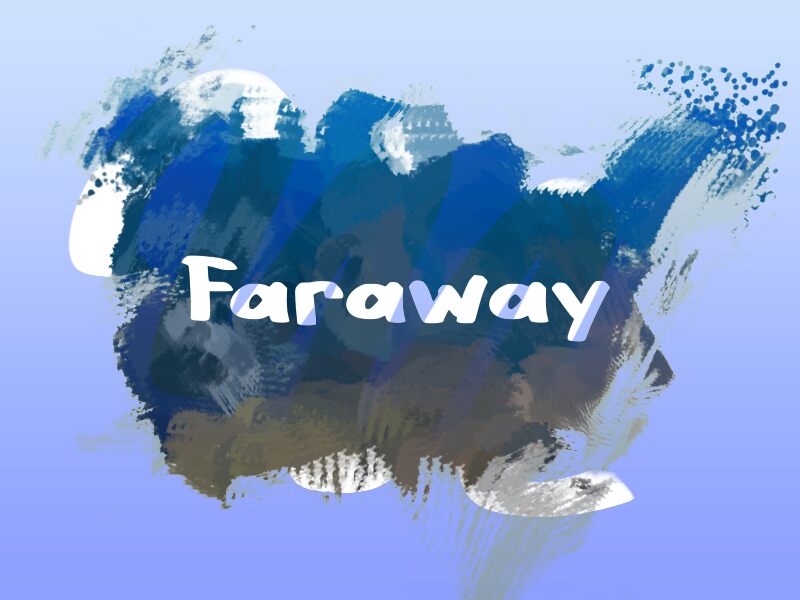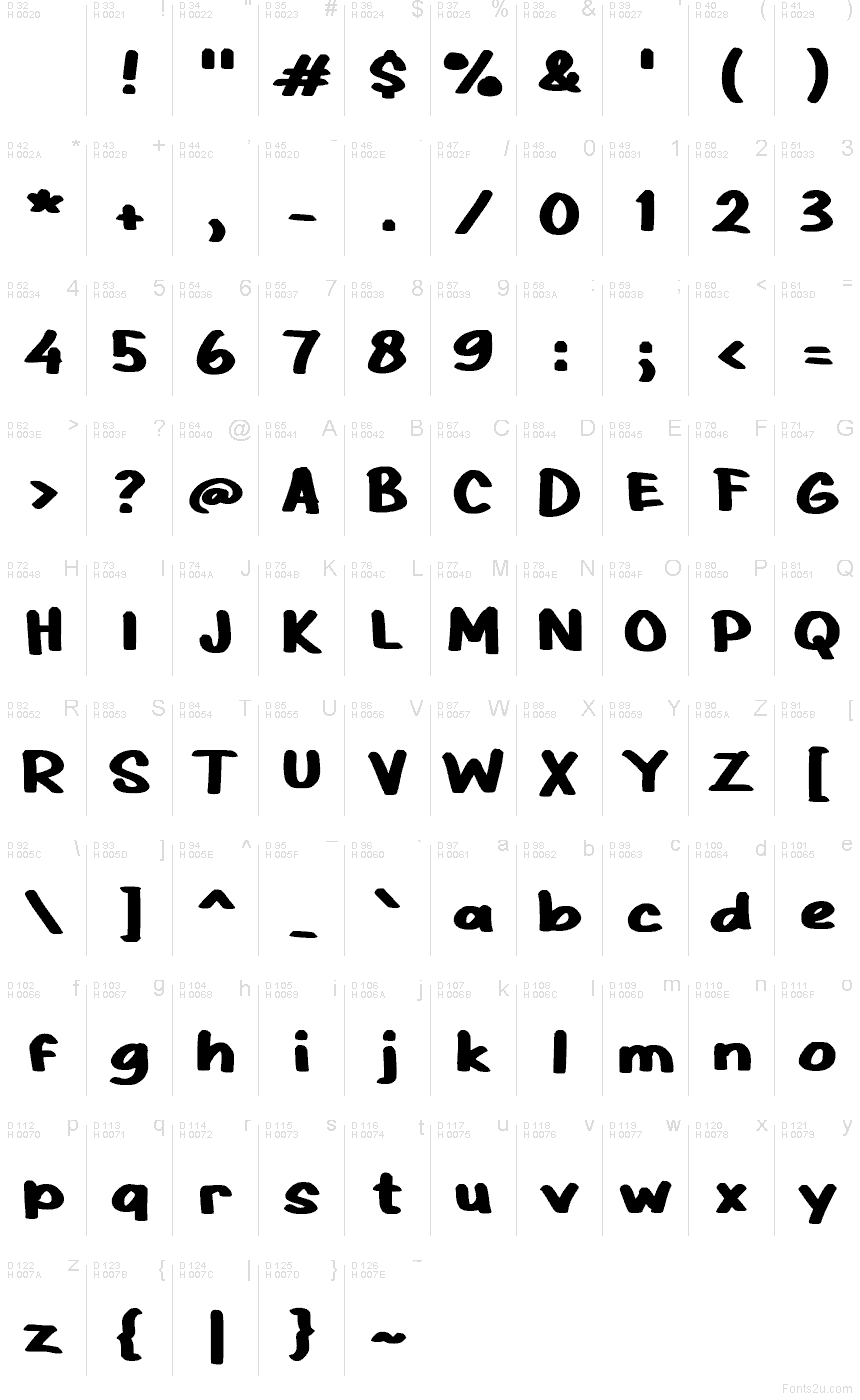
Faraway
Faraway от Wep — это бесплатный рукописный шрифт, массивный и с лёгким «мультяшным» характером. Буквы выглядят мягкими и живыми благодаря толстым скругленным штрихам, слегка неровным формам и естественной небрежности, которая не дает тексту выглядеть слишком строгим или «компьютерным».
Шрифт отлично подходит для оформления весёлой упаковки, детских книг, логотипов кофеен, постеров и заголовков в соцсетях, где дружелюбие важнее формальностей. Как бесплатный шрифт, Faraway лучше всего работает в коротких фразах, эскизах логотипов и крупных заголовках: его крупные, «дутые» буквы придают даже самым простым словам легкий и аутентичный рукописный вид.